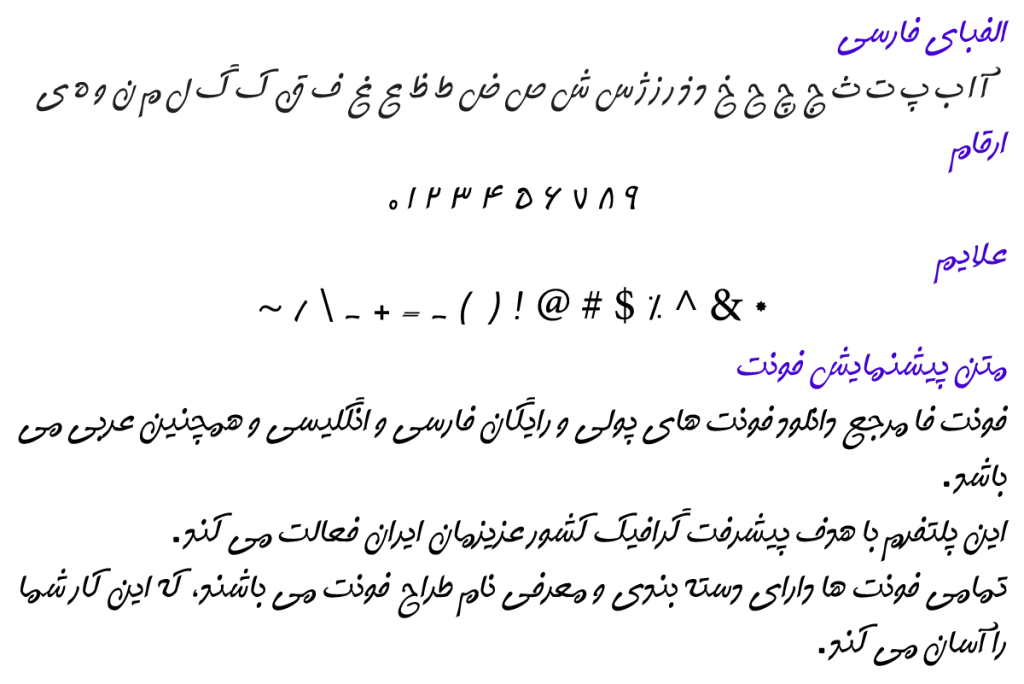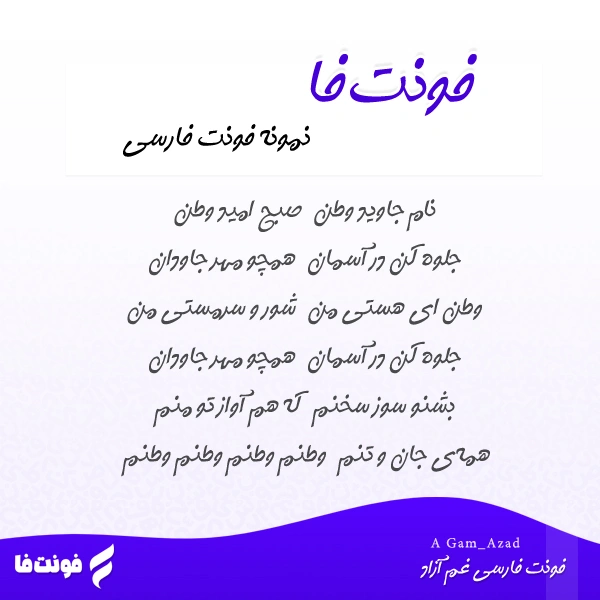
فونت فارسی غم آزاد – A Gam Azad
سال ساخت فونت: 1391
طراح فونت: مجتبی کیا نوع فونت: فونت دست نویس
پیشنمایش فونت غم آزاد
توضیحات و معرفی فونت غم آزاد
فونت فارسی غم آزاد ( A Gam Azad ) از مجموعه فونت های آزاد می باشد، و نیز نوع فونت دست نویس می باشد.
فونت خوشگل مربوط توسط مجتبی کیا در سال 1391 طراحی و ساخته شده است.
و نیز فونت A Gam Azad در یک وزن معمولی است.
در تصویر زیر پیش نمایش این تایپ فیس را مشاهده میکنید.